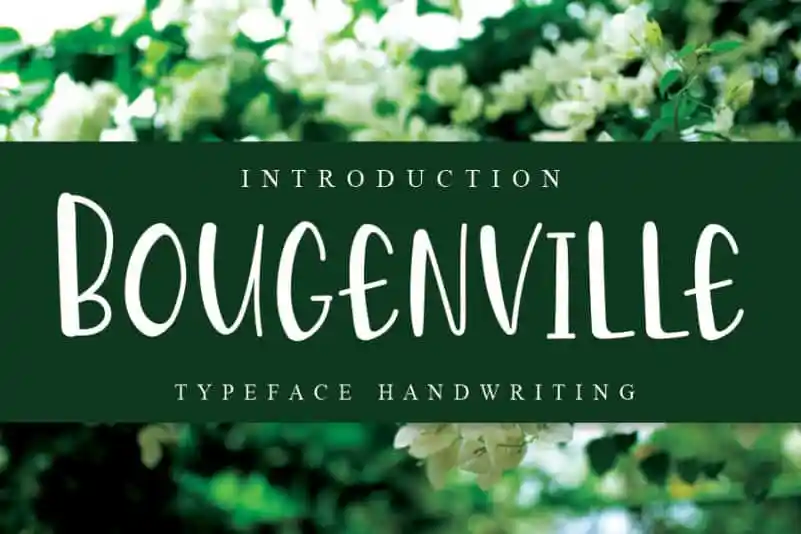
Bougenville Display Font – Fonte Grátis
Bougenville Display Font
A fonte Bougenville Display é uma escolha ideal para quem busca uma mistura divertida e amigável que deixará cada projeto impresso destacar-se. Especificamente projetada como um estilo de letra exibido, esta fonte consegue capturar a essência casual e descontraída com perfeição. Seja em cartões personalizados, logotipos criativos ou até mesmo as letras de mensagens de texto, Bougenville Display irá adicionar uma pitada divertida que ajudará qualquer projeto a se destacar no mundo digital. Ideal tanto para quem busca um toque único quanto para designers que desejam criar design gráfico mais descontraído e acolhedor, esta fonte é certamente uma opção imperdível. Através de sua elegante apresentação casual, Bougenville Display irá tornar suas criações ainda mais memoráveis.